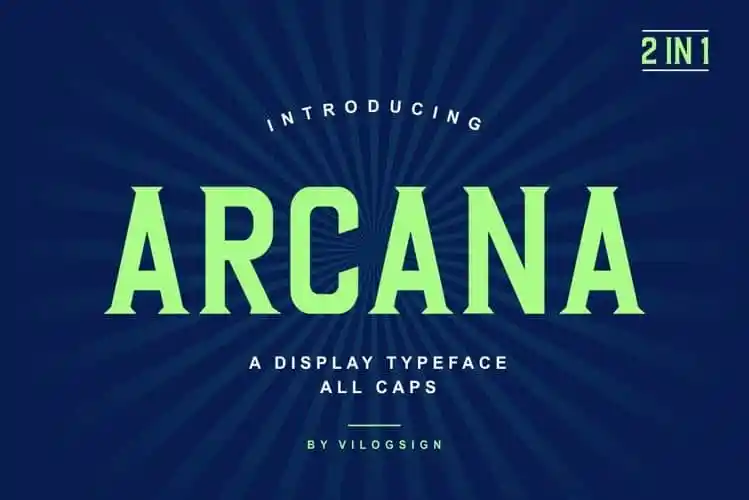
Arcana Display Font
Arcana Display Font é uma opção perfeita para adicionar um toque moderno e forte à sua identidade visual. Esta fonte sans-serif é ideal para títulos, garantindo impacto e alta visibilidade no seu design. Com seu estilo bold moderno e com letras em maiúsculas sólidas, Arcana Display Font se destaca como uma solução multiuso ideal tanto para aplicações digitais quanto impressas. Seu formato único de fonte dupla permite a você criar um contraste impressionante entre subtítulos e texto principal, tornando-a uma escolha perfeita para qualquer projeto que exija alta relevância visual. Uma escolha inteligente para designers buscando transmitir poder com cada letra.